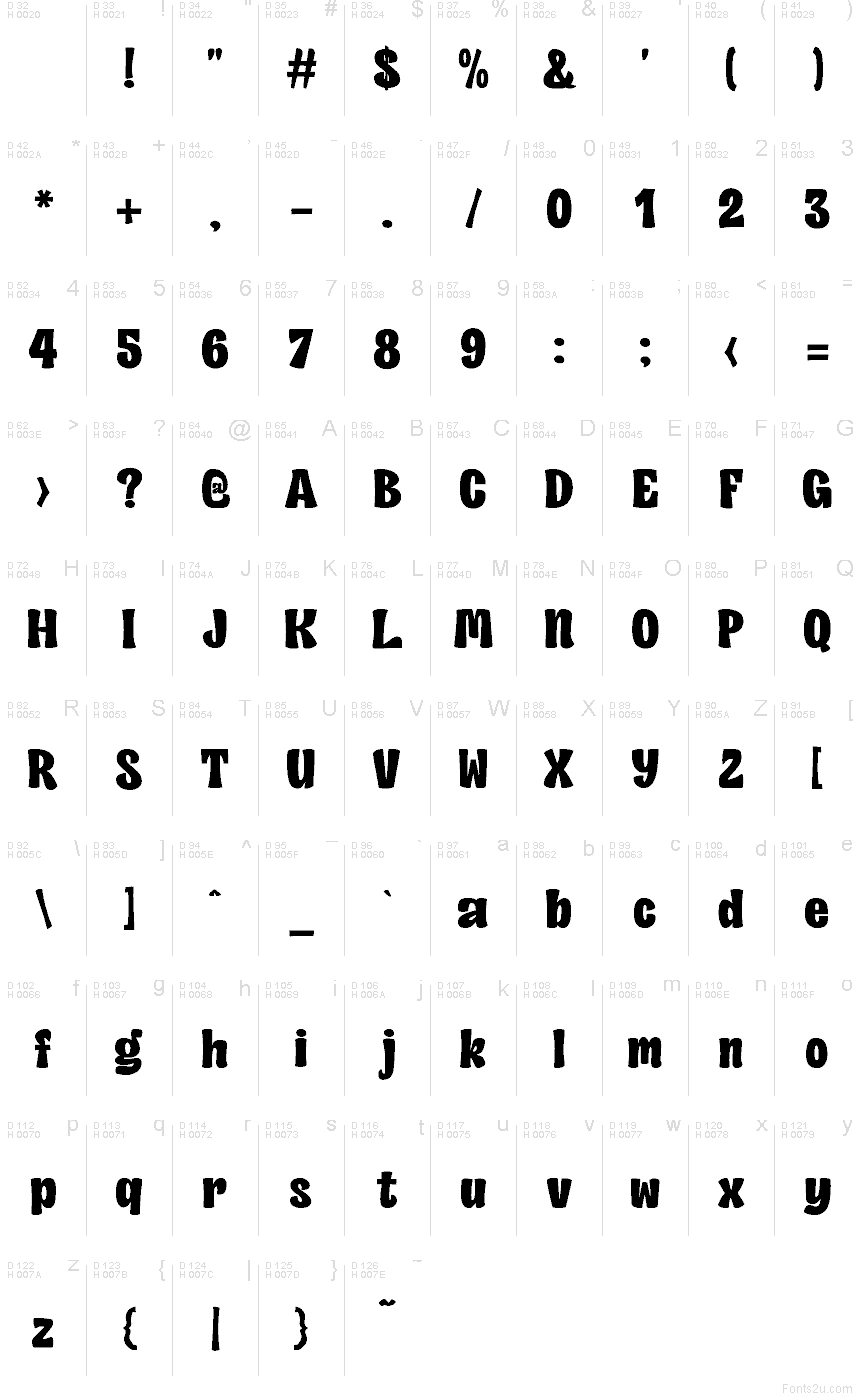
Le Chocolat Qui Fait Sourire od BlackFridayFont je bezplatné display písmo s vysokou, hravou siluetou, která se přirozeně rozšiřuje a zúžené tvary se střídají mezi jednotlivými písmeny. Toto nerovnoměrné střídání dává písmu přátelský rytmus s měkkými, zaoblenými tvary, které působí jako ručně modelované, nikoliv mechanicky vykreslené.
Nejlépe vynikne na obalech, v kavárenských menu, při brandingu cukrovinek, v titulcích plakátů nebo na grafikách pro sociální sítě, kde může naplno zazářit vřelý a výrazný nápis. Díky svému baculatému a optimistickému vzhledu skvěle ukotví i nálepky, dárkové visačky nebo hravé cedule obchodů, aniž by přitom působil tuctově.